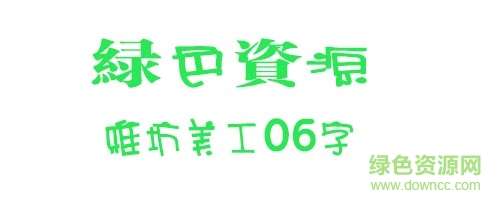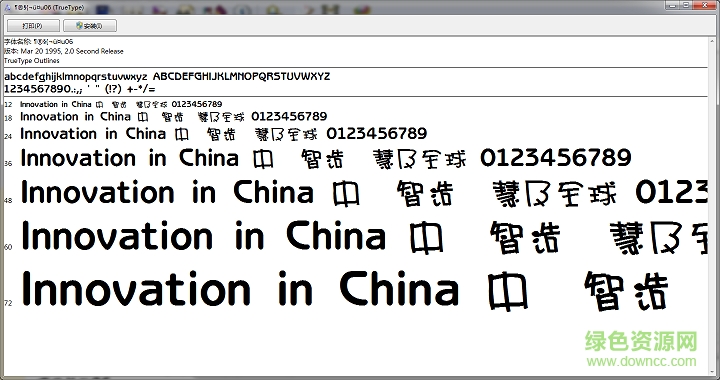
雅坊美工06是一款有點(diǎn)歪斜的中文字體。一般人可能用的不是很多,但是,美工朋友們就經(jīng)常用到了。有需要的朋友,趕快下載體驗(yàn)吧!
雅坊美工06是一款用于美工設(shè)計(jì)方面的字體,該字體端莊雄秀、神韻超逸、圓融蒼潤,看上去十分美觀,整體效果非常統(tǒng)一,且字庫完整,可以廣泛應(yīng)用于美術(shù)設(shè)計(jì)、企業(yè)LOGO、宣傳海報(bào)、ppt、影視制作以及內(nèi)容用字等領(lǐng)域